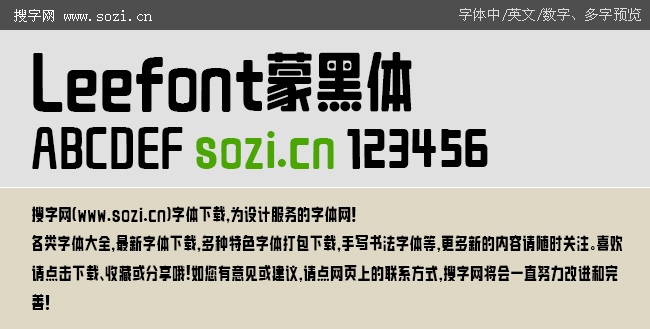
Leefont蒙黑體
搜字網(wǎng)給大家提供一款Leefont蒙黑體中文字體下載,樂字蒙黑體(Lee font蒙黑體)是“LeeFont(樂字)”制作的一款免費(fèi)美術(shù)標(biāo)題字。樂字蒙黑體整體字形偏長(zhǎng),字面結(jié)構(gòu)飽滿,有穩(wěn)重中具備力量感的同時(shí)筆畫結(jié)構(gòu)蘊(yùn)含樂趣在其中,使其多了一些生動(dòng)活潑。。適合應(yīng)用于藝術(shù)設(shè)計(jì)、平面宣傳設(shè)計(jì)、網(wǎng)頁設(shè)計(jì)、海報(bào)設(shè)計(jì)等應(yīng)用。